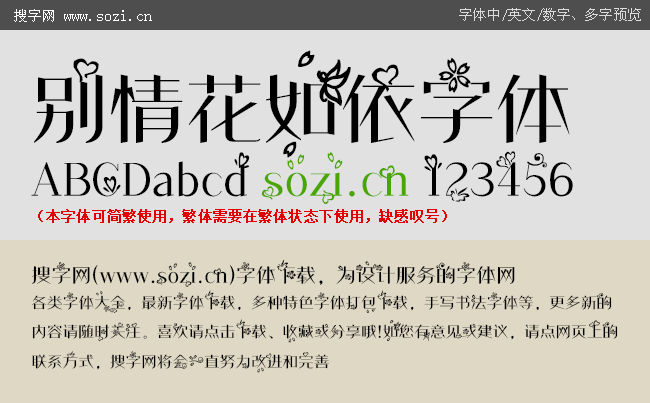
別情花如依字體
搜字網(wǎng)給大家提供一款很精致的手機(jī)中文字體下載。別情花如依字體,這款手機(jī)字體是在方正明尚簡(jiǎn)體字體筆畫(huà)間插入了可愛(ài)漂亮的花紋圖案。十分精致,該手機(jī)字體個(gè)性實(shí)足,趣味性強(qiáng),又保持了文字的識(shí)別度,特別適合喜歡手機(jī)字體個(gè)性一些的女生在手機(jī)上安裝使用。